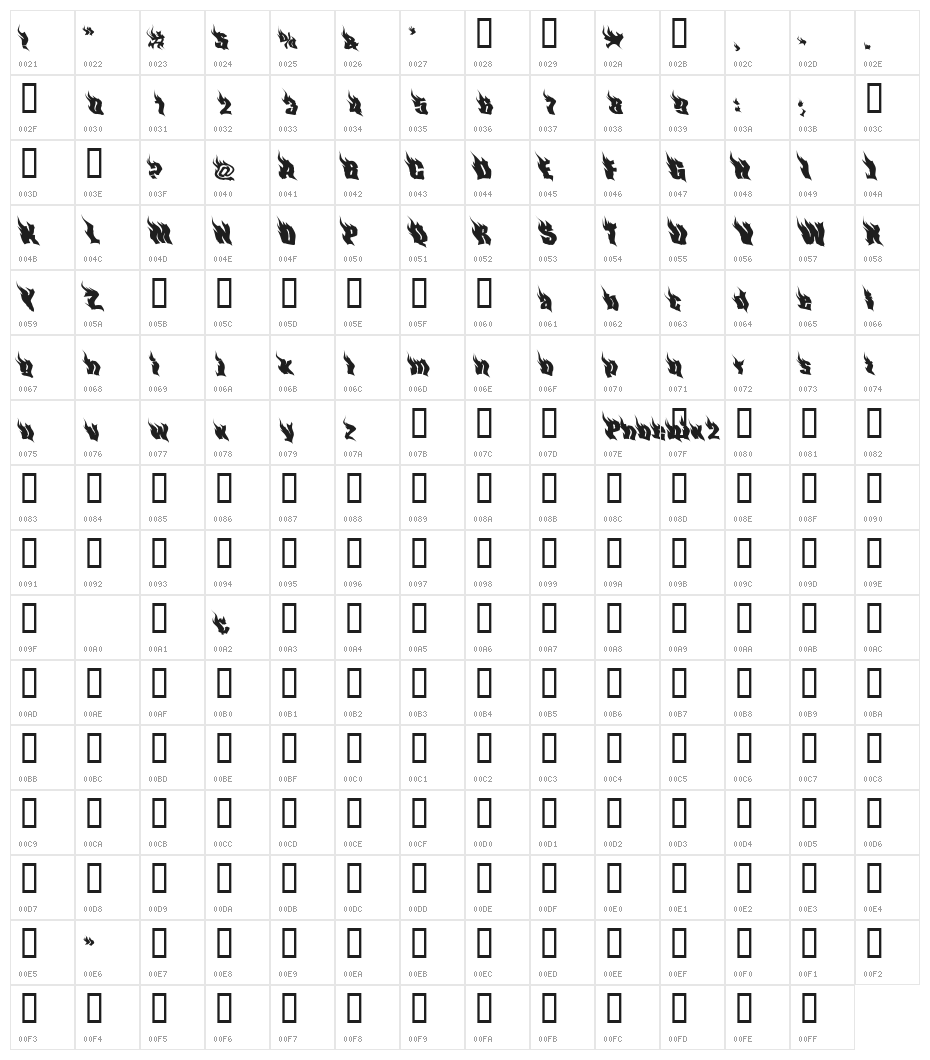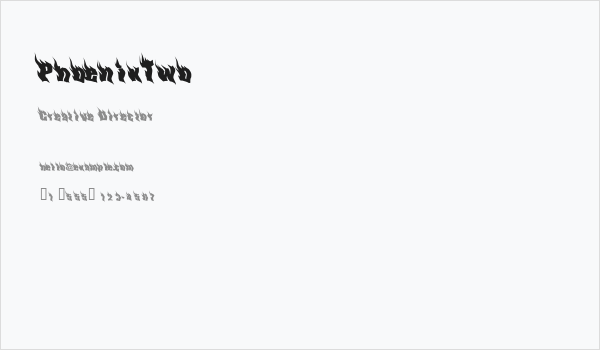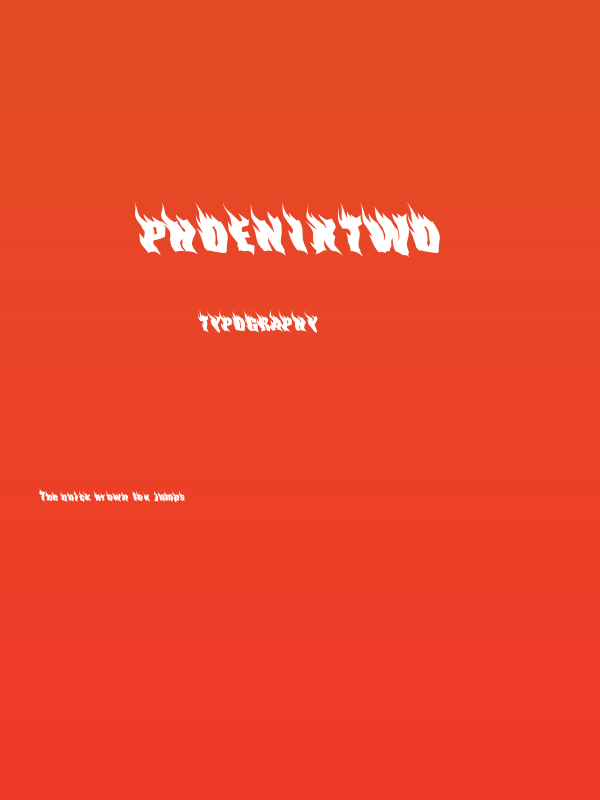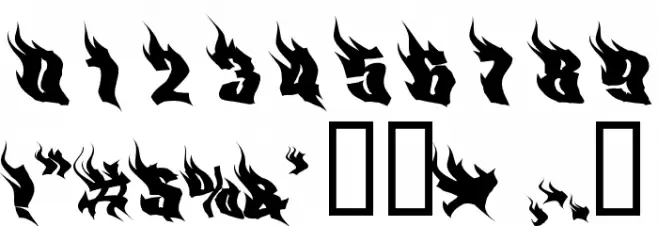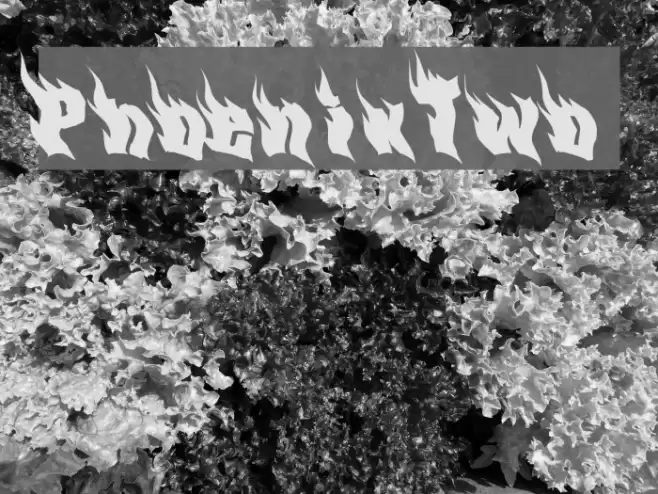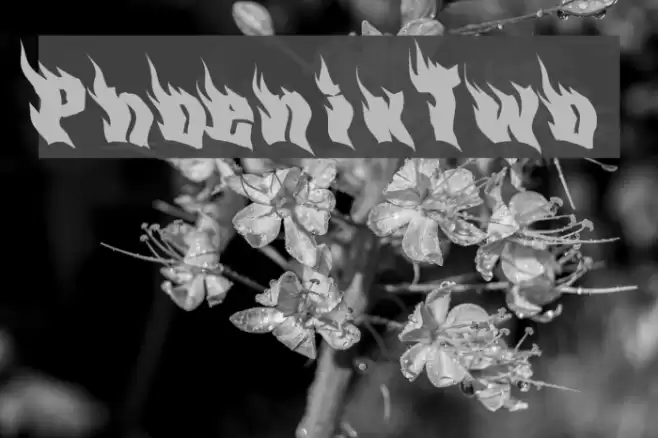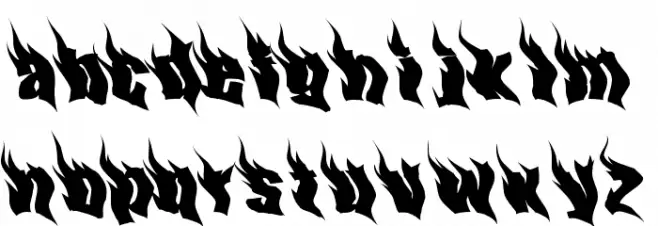
PhoenixTwo Font
| おすすめプロジェクト | Ideal for projects that require a striking and energetic visual impact, such as music album covers, event posters, or branding for extreme sports. |